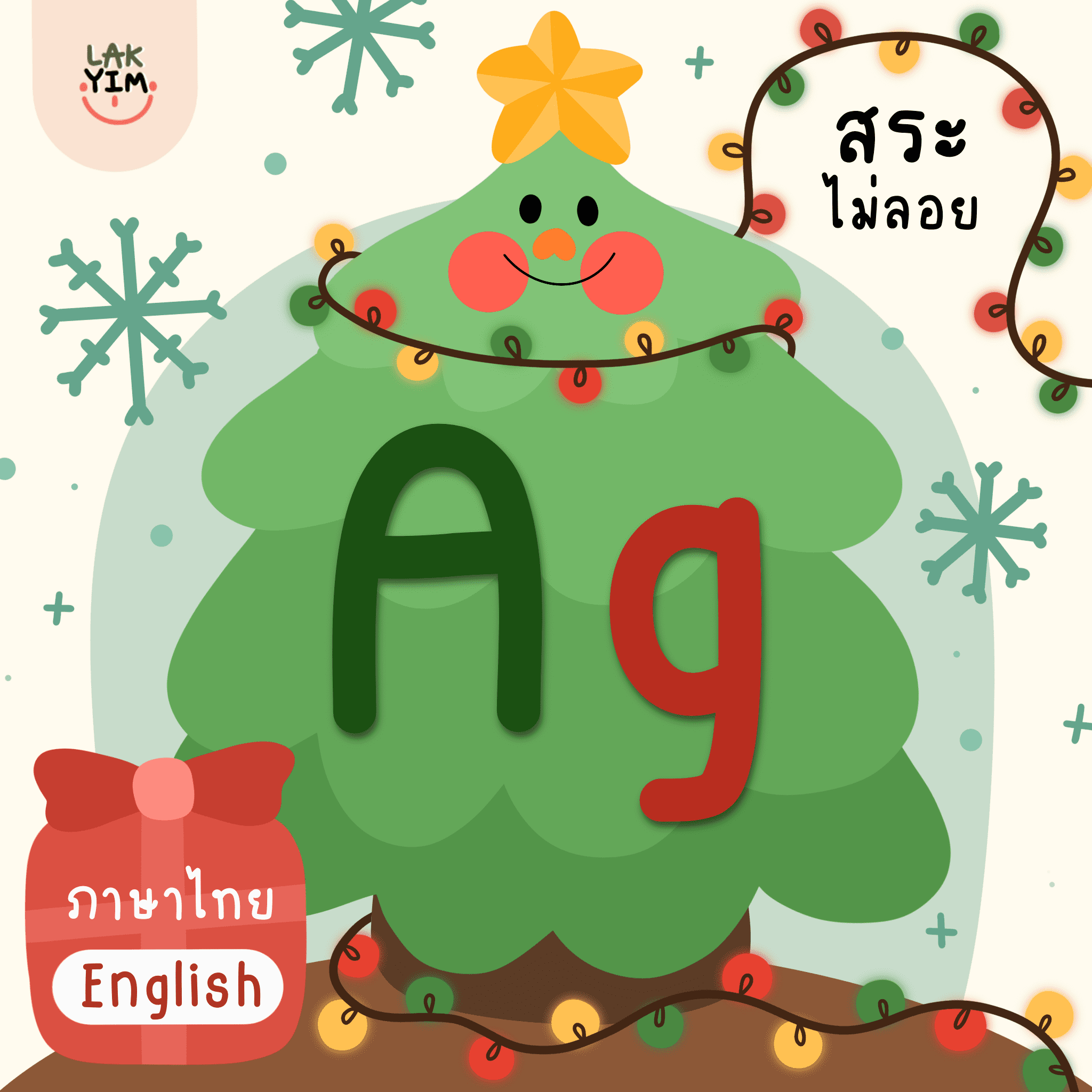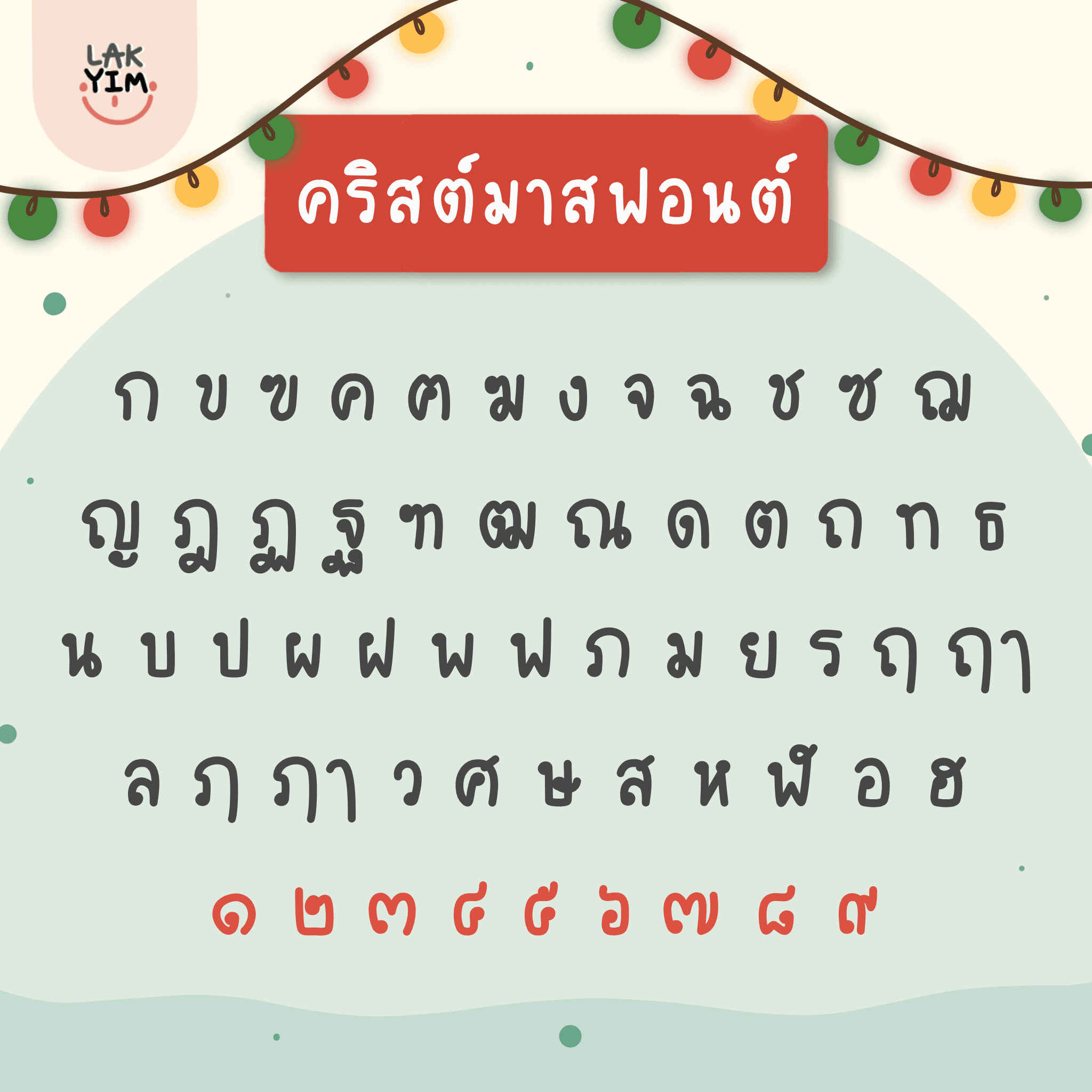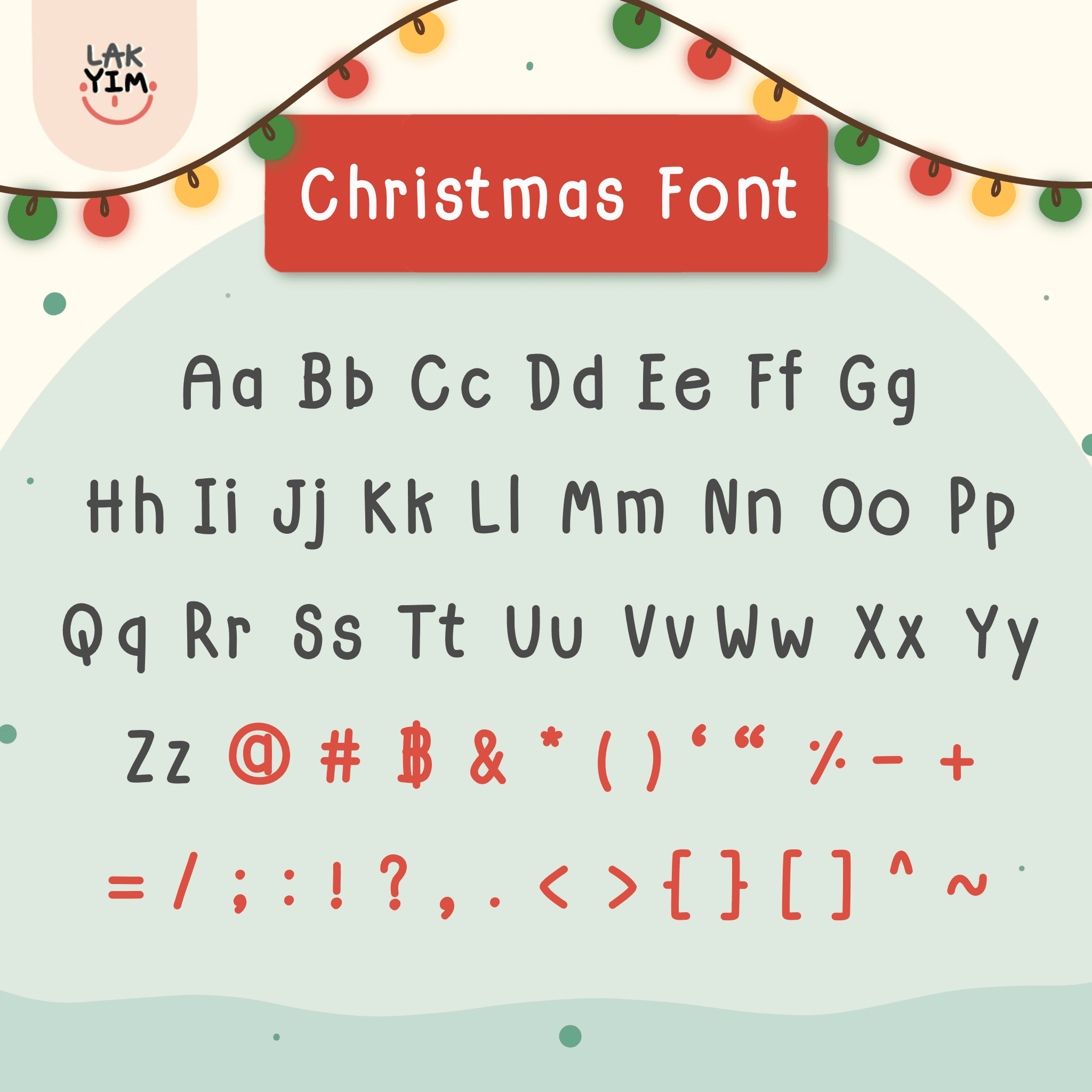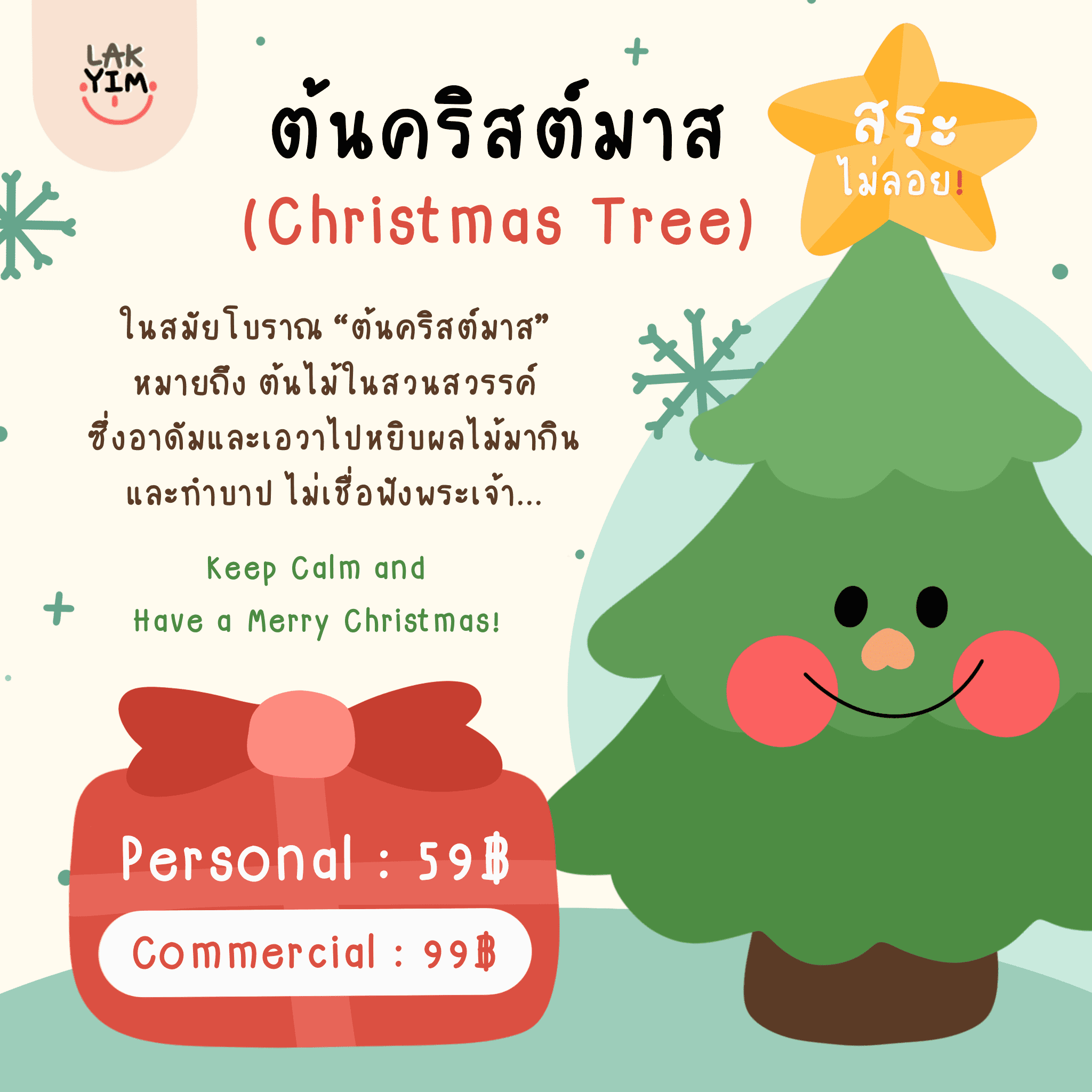
LAKYIM.OFFICIAL | FONT (CHRISTMAS FONT)
ฟอนต์ลายมือแบบตัวบางหนา มีความน่ารักอบอุ่นเข้ากับเทศกาลคริสต์มาสมาก ๆ
ทั้งยังอ่านง่าย สบายตา เหมาะกับการเอาไปใช้เขียนบันทึก หรือทำชีทสรุป 🗒️✨
📍ที่สำคัญ: สระ ไม่ ลอย ‼️‼️
– มีทั้งภาษาไทยและภาษาอังกฤษ